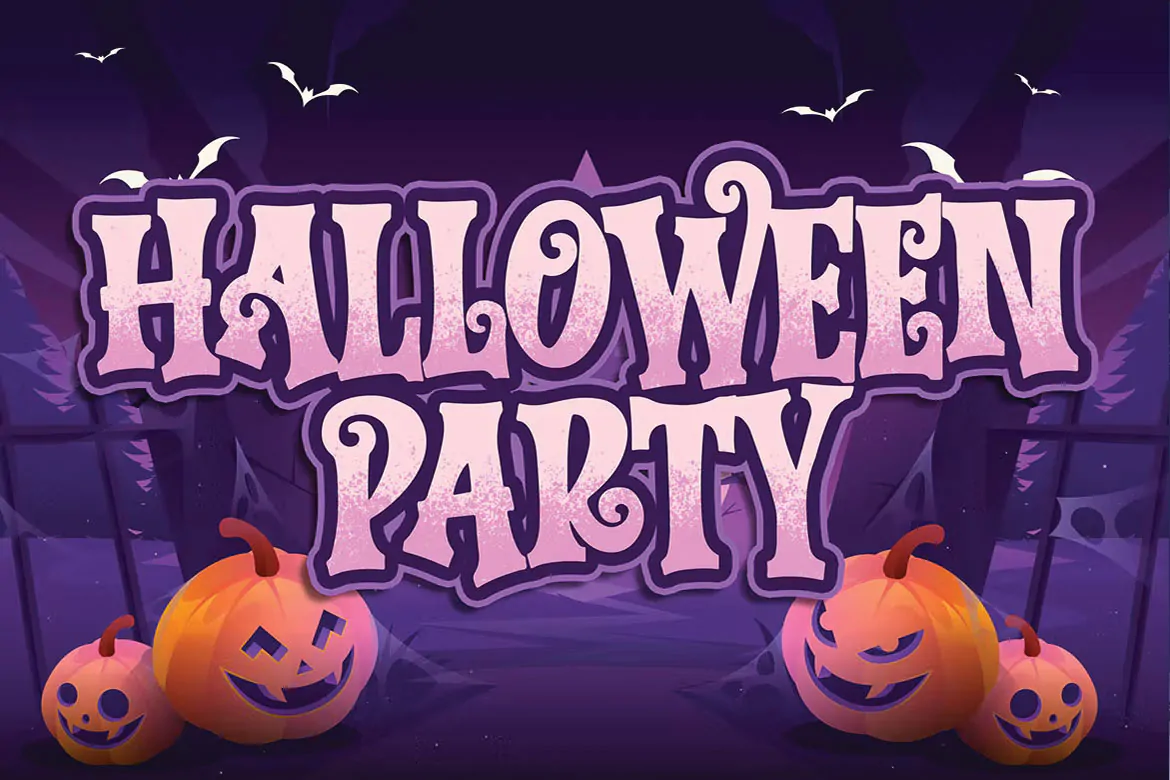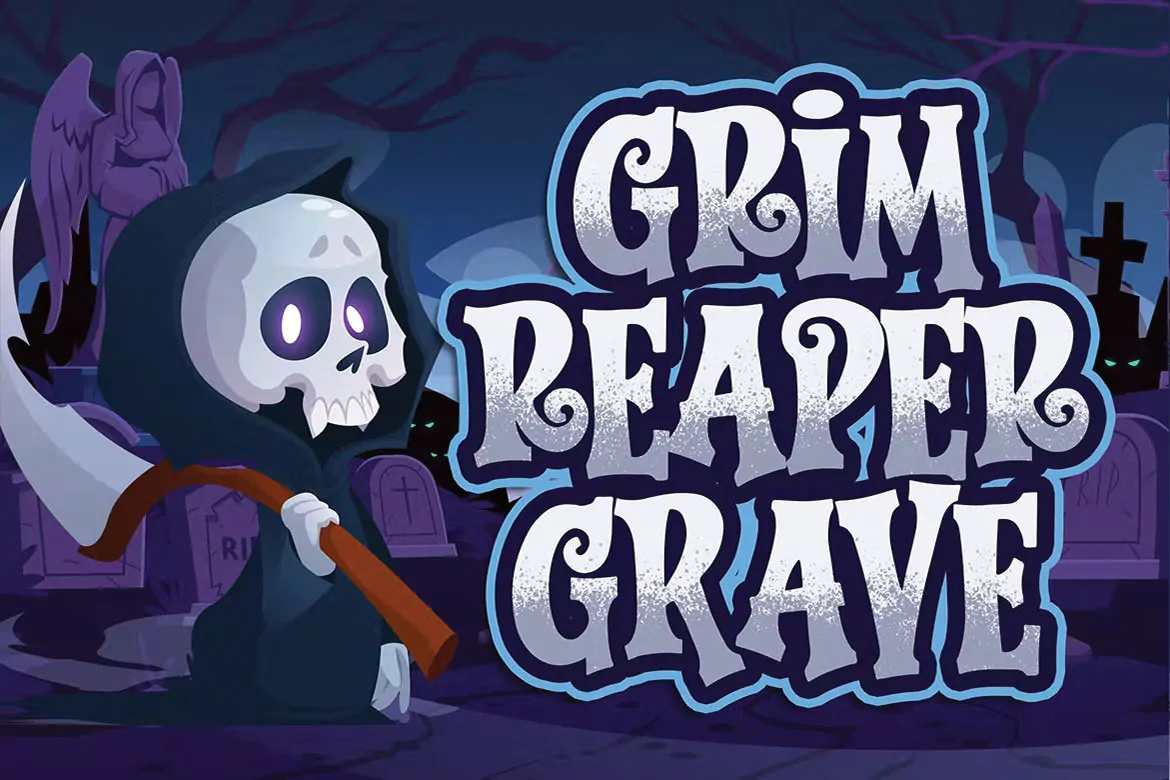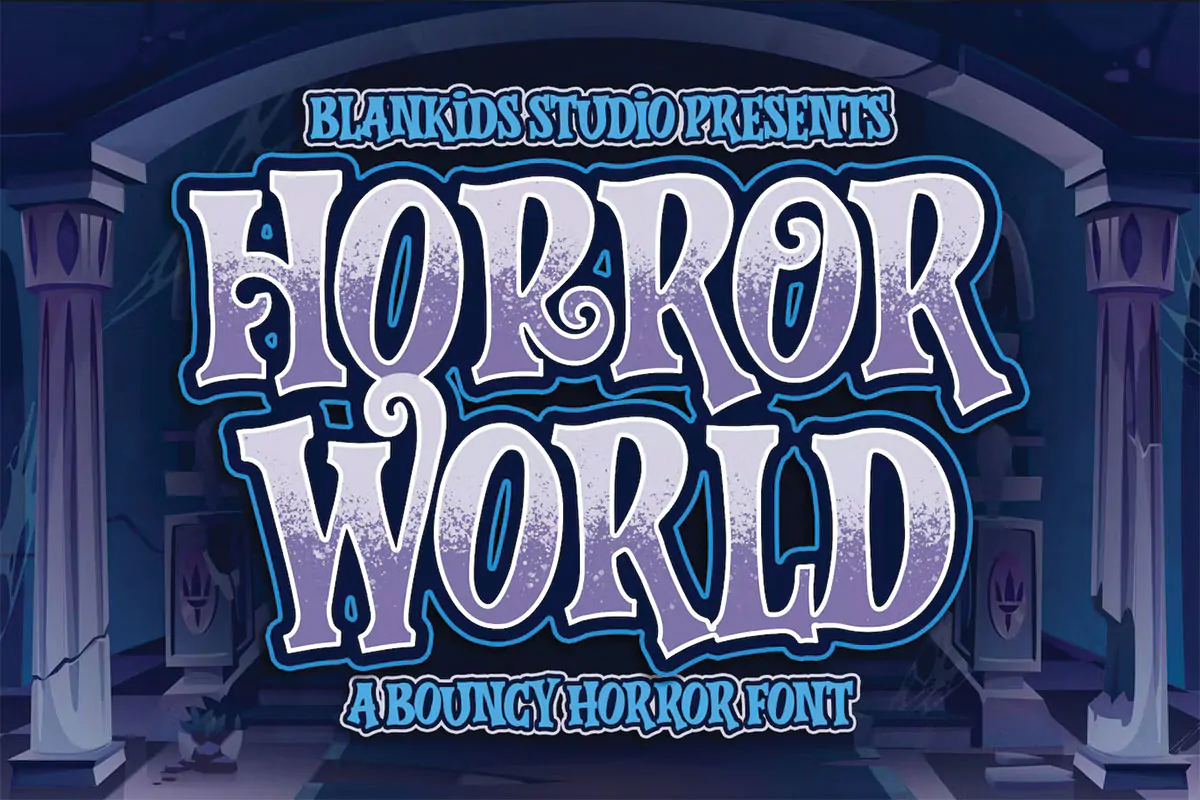
فونت ترسناک با استایل فنری Horror World
فونت ترسناک با استایل فنری انگلیسی
فونت ترسناک با استایل فنری Horror World یک قلم سنس سریف انگلیسی است که مناسب برای استفاده در طرح و پروژههای گرافیکی مختلف همچون طراحی پوستر، بنر، تقویم، بسته بندی محصولات، ظروف یکبار مصرف، لوازم التحریر و … میباشد.